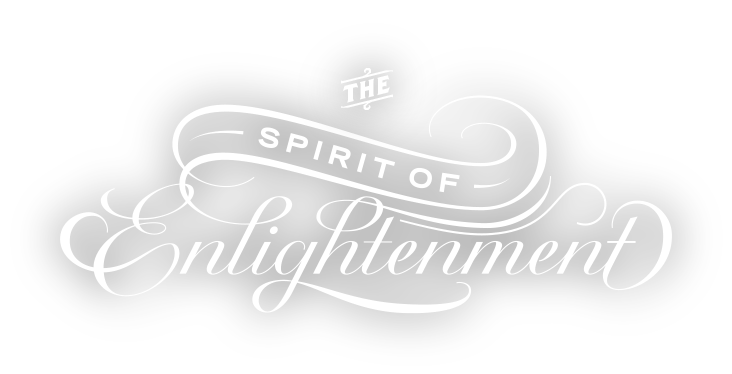
Welcher Script könnte das sein
Ein solches E ist mir noch nicht untergekommen und der Schnörkel vom l passt prima zum Band von "Spirit of". Daher vermute ich, dass zwar eine Script zugrundeliegt, aber das letztendlich Handarbeit ist.
ja, das denke ich auch !!! Kennt ihr denn ne Script mit ähnlich vielen Glyphen wie die Burgues Script?
Die Biscotti ist es leider nicht :(
Ich habe das vorher leider nicht ausprobiert :-D. Aber auch ich glaube, dass es aus der Hand eines Designers stammt.
Ich vermute aber, dass die ITC Edwardian Script auch ähnlich viele Glyphen hat wie die Burgues Script:
Die Biscotti Bold kommt dem schon recht nahe. Leider gibt es diese nicht mehr auf myfonts.com.
Die Biscotti kommt von Cyrus Highsmith. Er hat sie vormals via Font Bureau angeboten (bzw. typenetwork.com) seit neuestem über sein eigenes Label Occupant Fonts und ist KEIN freefont! Übrigens: Die Font-Bureau-Schriften sind schon seit längerem nicht mehr auf MyFonts.com gelistet. Warum, weiß ich nicht.